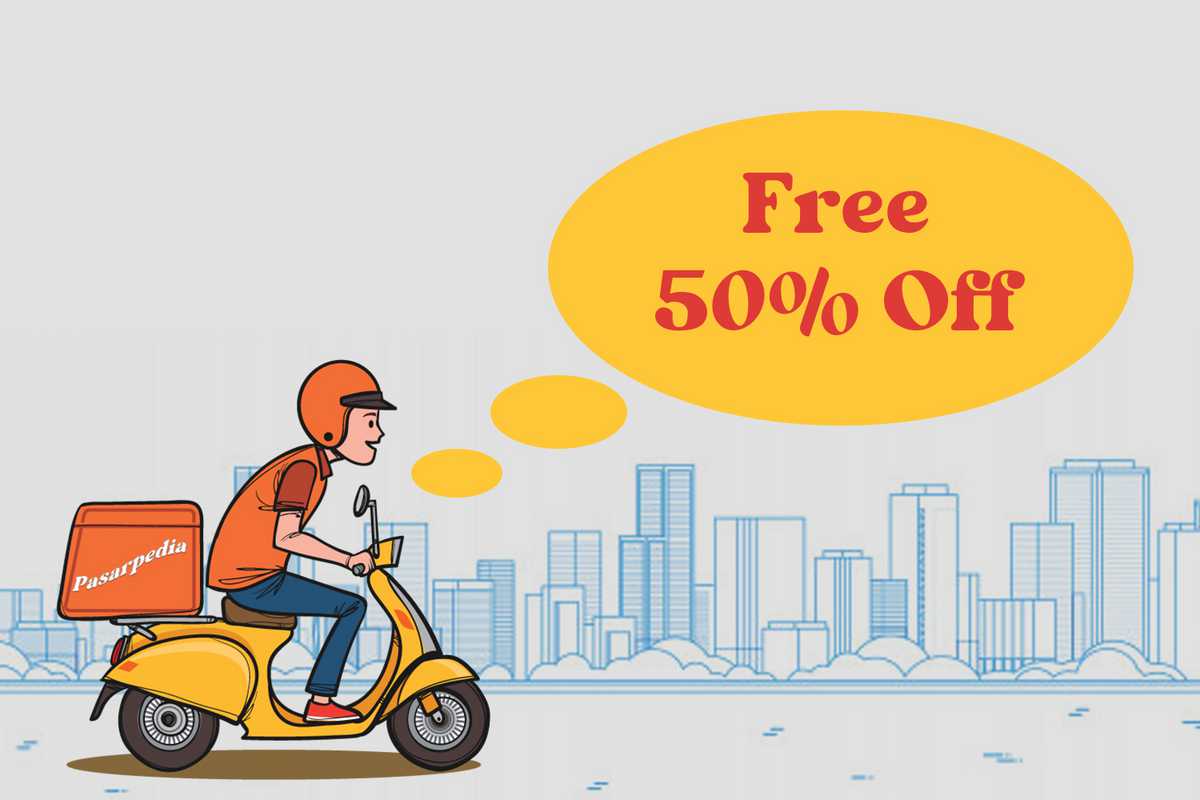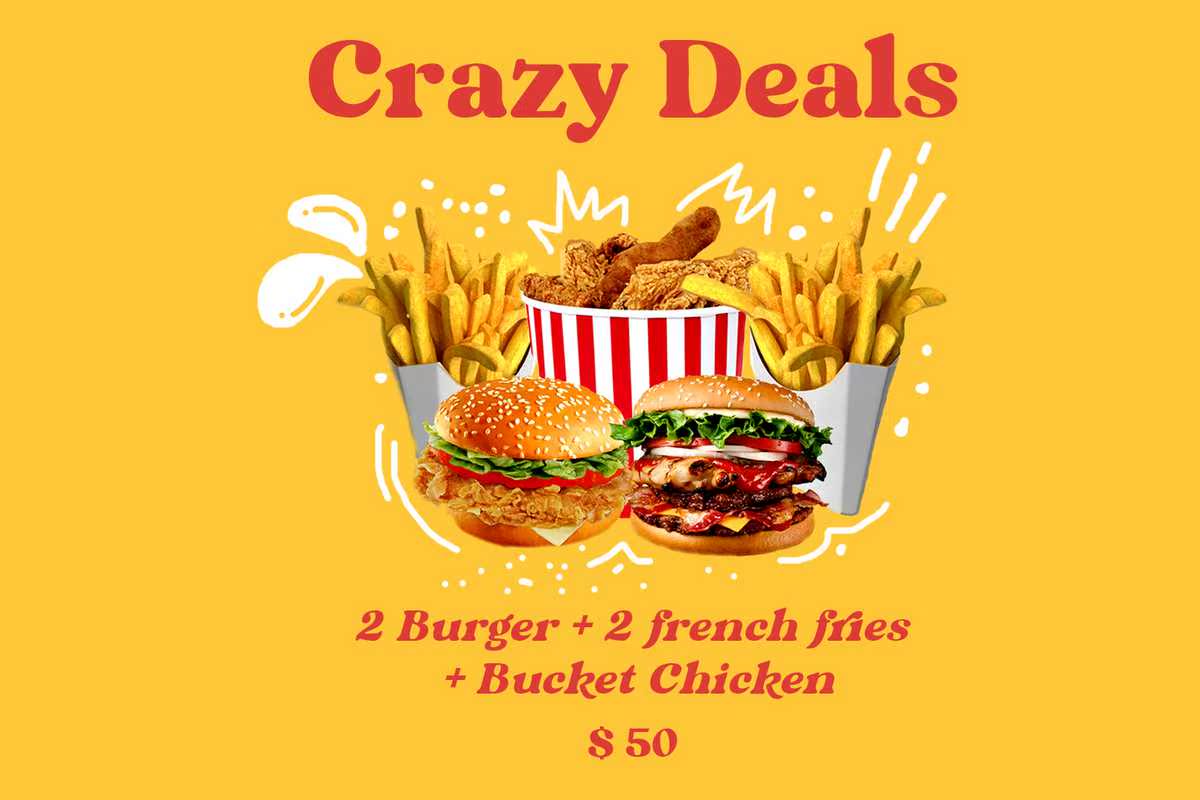
Vikendi isabold,现代和ClassyStyle中的圆形脚本字体。OpenTypeFeatures包括ldStyleFigures和Ligatures。Vikendi适用于标题、标题、徽标、标签、包装、明信片、演示、杂志、邀请函等。Vikendi isabold,Modern and ClassyStyle中的圆形脚本字体。OpenTypeFeatures包括LDStyleFigures和Ligatures。Vikendi适用于标题、标题、徽标、标签、包装、明信片、演示文稿、杂志、邀请函等。